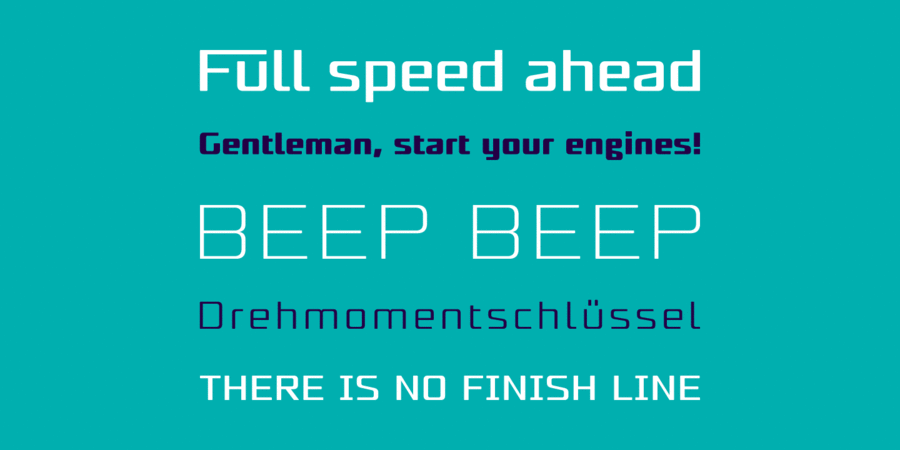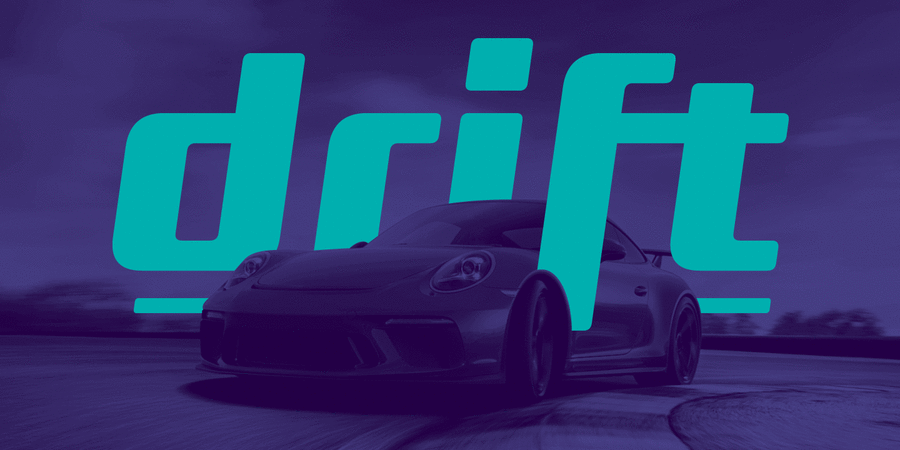
Опис гарнітури NafteraЦе механічний геометричний гротеск з розчерками та злегка заокругленими кутами, які надають серйозний, але вишуканий вигляд. Naftera була задумана як шрифт для логотипів, заголовків та елементів екранного інтерфейсу, а також для коротких текстових блоків. Сімейство складається з 10 накреслень. 8 накреслень містять величезну кількість гліфів для різних мов, включно з кирилицею, а також капітель та лігатури. Інші 2 накреслення безкоштовні для використання на умовах десктоп-ліцензії. Шрифт розробив Пабло Балселлс у 2019 році.
Особливості сімейства шрифтів NafteraХіт десятиліття:
Асоціації з сімейством шрифтів NafteraОсобистість і характер гарнітури:
рівний, точний, логічний, автоматичний, техногенний, твердий, статичний, чіткий, стійкий, стабільний, тонкий, легкий, міський, сучасний, машинний, інженерний, урбаністичний, креслярський, скляний, крихкий, футуристичний, прозорий, спокійний, дротяний, худий, гладенький, гнучкий, чистий, модний, лаконічний, неоновий, надійний, впевнений, сталевий, байдужий, переконливий, серйозний, сильний, індустріальний, залізний, промисловий, залізничний, сексуальний, швидкісний, гоночний, рішучий, спортивний, енергійний, комп'ютерний, крутий, амбітний, кінематографічний, сміливий
конструктор, креслення, архітектура, інженер, автоматика, урбаністика, Місто, гаджет, електроніка, технології, інновації, дизайн, статистика, інструмент, гра, прилад, айтішник, IT, айті, андроїд, залізо, фантастика, авто, промисловість, техніка, вагон, транспорт, залізниця, комп'ютерна гра, інтернет, мобільний зв'язок, девайс, автомобіль, кіно, нафта, паливо, енергетика, електростанція, гонки, ралі, формула 1, тачки, спорт, комп'ютер, швидкість, супергерой, кіберспорт, селфі, шолом, машинобудування, автобус, тренажери, Доставка Гарнітура асоціюється з віком: